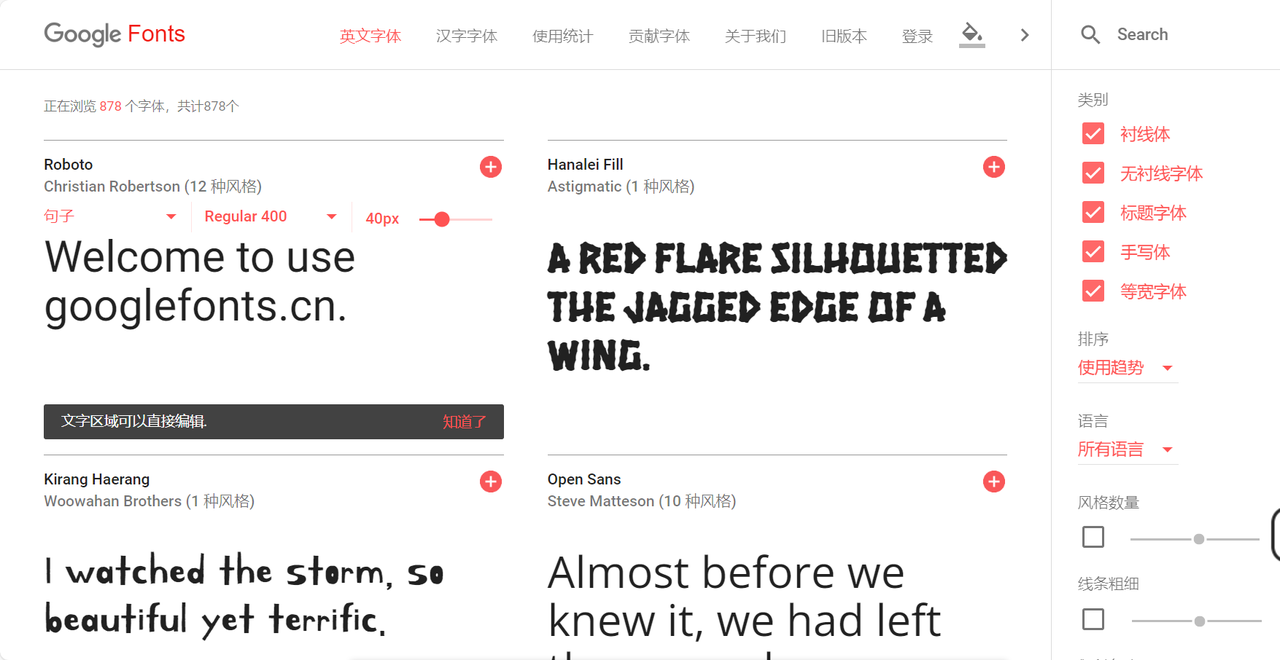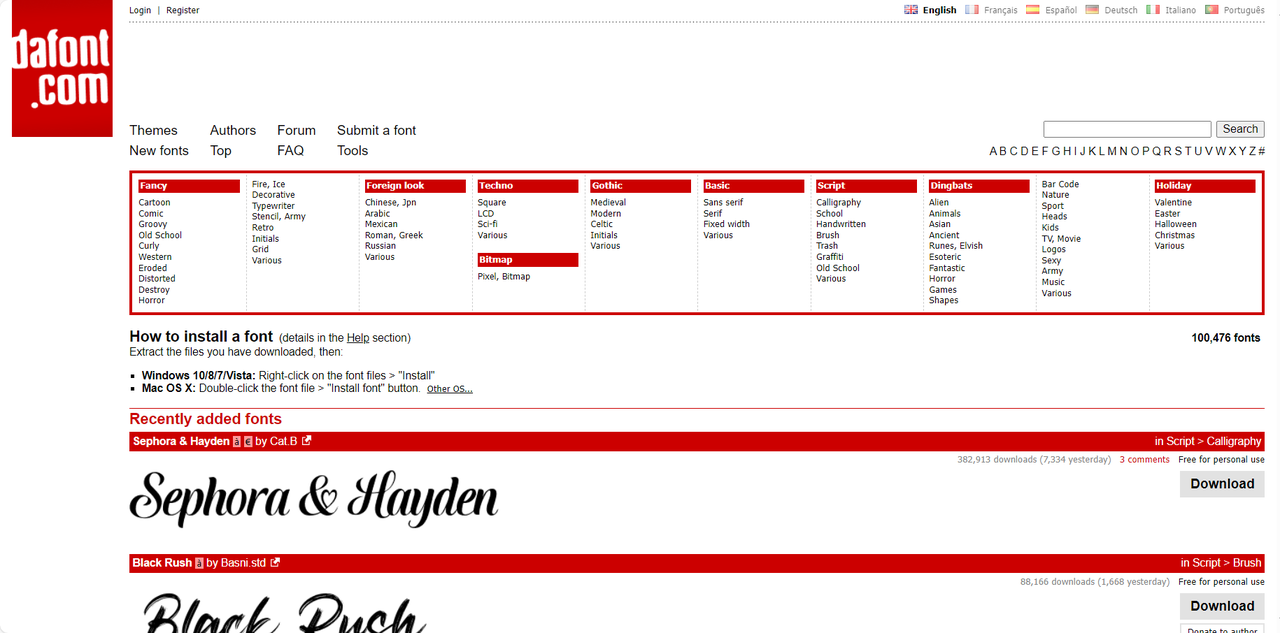
设计不够出彩?码住这几个艺术字字体下载网站!
总觉得自己做的海报差点意思,明明构图配色都花了心思,可是就觉得作品不够出彩?别慌!多半是你没选对合适的字体!字体对于设计行业来说是非常重要的一个存在,它能有效提升作品的质感以及美观性。设计不够出彩,艺术字字体下载网站就是最大的救星!今天给大家整理了 5 个宝藏艺术字字体下载网站,字体不仅免费可商用,而且风格多样,不会有任何版权纠纷哦,新手也能轻松获得吸睛艺术字字体,让你的设计瞬间提升一个等级,赶紧码住备用。
一、字由
字由是设计师圈子里公认的宝藏字体平台,尤其是它丰富的字体资源库简直就是艺术字爱好者的天堂。字由收录了上万款字体资源,其中也包含风格各异的艺术字字体,几乎覆盖了所有设计场景的需求。为了便于大家快速定位自己想要的字体,用户可以根据字体风格、用途、品牌等多个维度来筛选艺术字。而且字由支持在线预览,也就是说输入自定义文字后可以实时查看字体呈现效果,如果你觉得符合你的预期再下载使用该字体也来得及。不过我个人认为,字由最大的优势还是字体的版权保障,网站上的大部分字体均来自正版字库,每款字体都清晰标注了它的授权方式,比如免费商用、会员商用等等,避免了无版权字体带来的侵权风险。不仅如此,字由的 AI 字体功能更是新手小白的福音,只需要找到一个自己喜欢的艺术字风格,点击“做同款”,30s 内就可以获得样图同款艺术字。这里的艺术字风格明显比资源库的字体更加张扬热烈,更能吸引你的眼球。
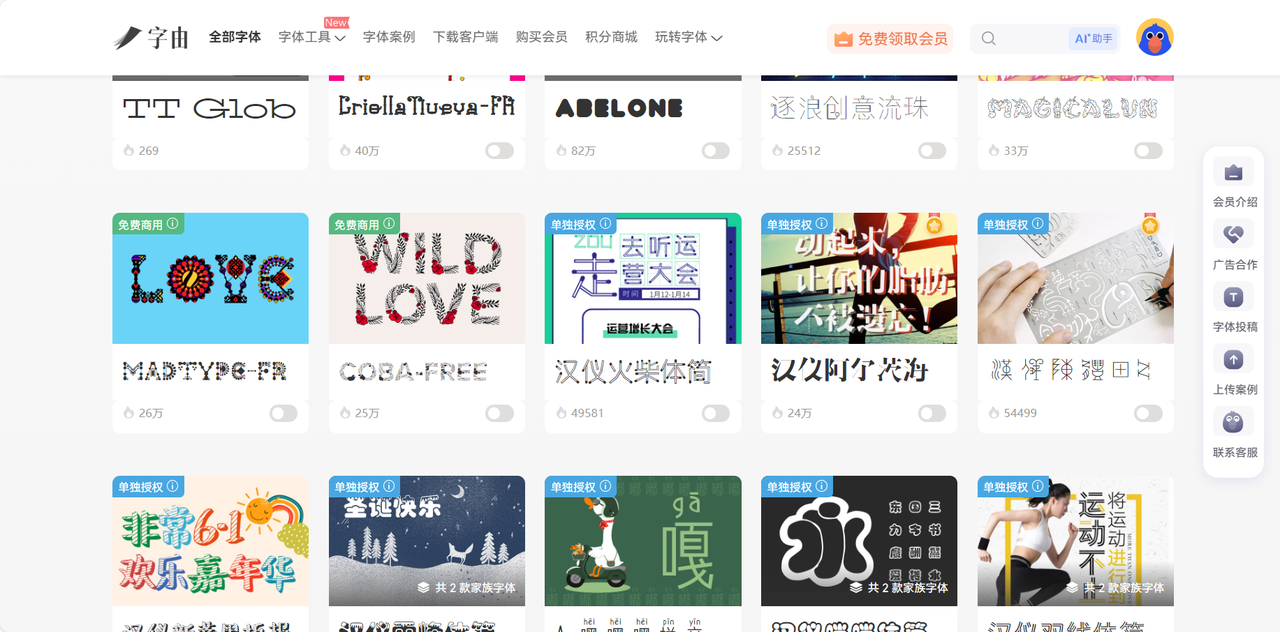
二、Google Fonts
Google Fonts 已经是个老生常谈的字体网站了,作为谷歌推出的免费开源字体服务平台,以资源丰富、无版权风险的特点赢得了全球设计师的青睐。官网的界面设计简洁清爽,用户的操作方式也一目了然,可以根据语言、字体类型、笔画粗细、流行度等方面筛选艺术字字体,在线实时查看预览效果。目前为止,Google Fonts 是我见过语言范围最广的,覆盖了英文、中文、韩文、日文、泰文等多个国家的字体资源,适合经常需要跨语言设计等设计师朋友们。下载流程也非常便捷哈,用户选择喜欢的字体之后,可以将字体下载为 TTF、OTF 等通用格式,能直接导入设计软件或安装到本地使用。值得一提的是,平台还提供了嵌入网页的代码,用户可以直接复制代码将字体应用到网站中,自动适配不同设备的显示效果,对网页设计师来说非常实用。
三、Dafont
Dafont 是国外知名的免费艺术字字体下载网站,也是全球最大的设计师分享平台。这里的字体资源都是由世界各地的设计师上传,当然也包含大量创意十足的艺术字,从复古怀旧的装饰体到未来感的科技艺术字,从可爱开通的手写体到潮流个性的涂鸦艺术字,不仅风格多,而且还是市面上比较少见的小众字体,有助于打造独特且个性的设计作品。和其他艺术字下载网站不同的是,Dafont 可以看到其他用户的使用案例和评价,很像所谓的买家秀,这也可以帮助你判断字体的实用性。不过需要注意的是,Dafont 上面的字体因为是用户自主上传,质量参差不齐,而且授权不一定清晰,建议大家选择下载艺术字之前仔细查看授权类型以及用户评价,优先选择下载量多且评价好的字体哈。
四、Font Squirrel
Font Squirrel 专门提供免费且能商用的艺术字字体,没有多余的广告和弹窗,用户体验非常流畅。如果说 Dafont 的字体质量参差不齐,那 Font Squirrel 的字体质量就太有保障了!平台上的字体都是经过人工审核,确保授权合规,个人或者商业使用都免费,让你不用再为字体版权问题发愁。字体资源库里的部分字体还提供了不同字重和样式的变体,方便用户在设计中灵活选择合适的字体。Font Squirrel 还设置了“热门商用字体”“精选艺术字字体”等板块,方便用户快速找到当下流行的商用艺术字字体,也能快速了解目前设计行业的风向,同时字体显示效果清晰,不论放大缩小都不会失真,非常适合商业项目。
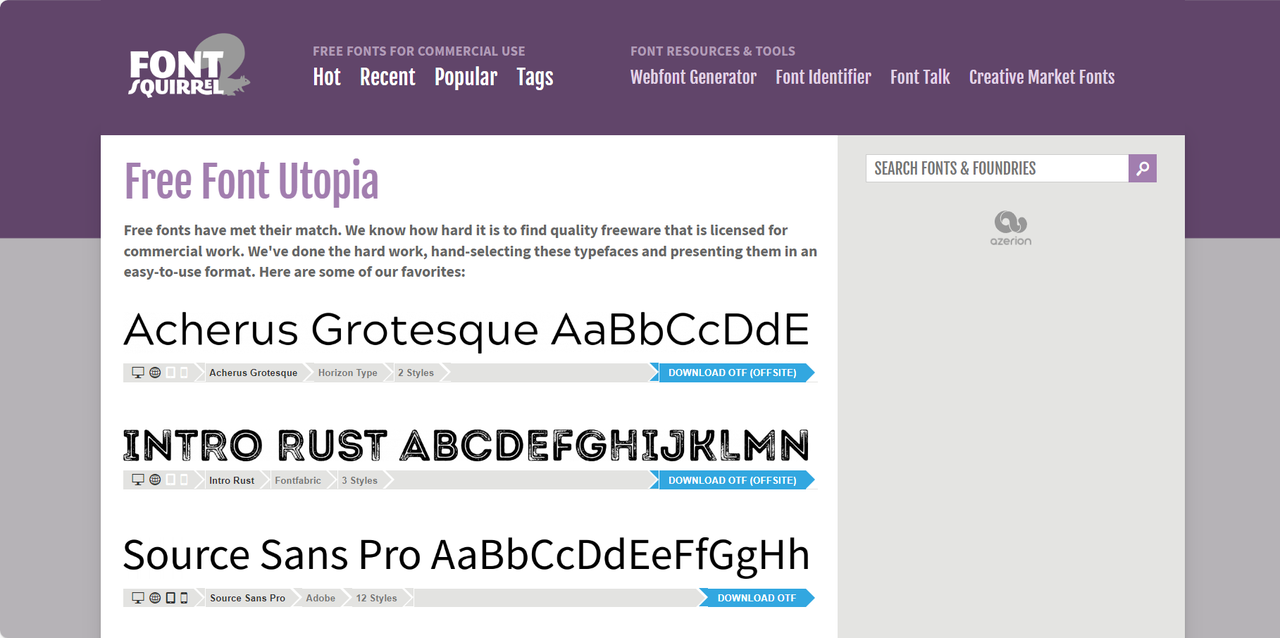
五、Urban Fonts
最后一个给大家推荐的艺术字字体下载网站就是 Urban Fonts,喜欢小众创意、潮流个性设计的小伙伴们一定要好好收藏码住!该网站收录了大量紧跟潮流的的艺术字字体,还搭配了潮流背景和排版示例,用户可以更直观地感受到字体的应用效果,非常适合做潮牌设计、文创包装、社交媒体配图等场景。Urban Fonts 最大的优势就在于定时更新热门风格的字体,紧跟设计行业潮流,所以很受年轻设计师和追求创意设计的用户喜爱。而且大部分字体都支持免费下载,其中不少字体还允许个人非商用使用哦,用户可以根据需求自行选择。为了便于大家下载字体,Urban Fonts 专门按照风格设置了字体合集,你可以选择直接下载整个字体合集,不同逐一挑选,节省了大量时间。